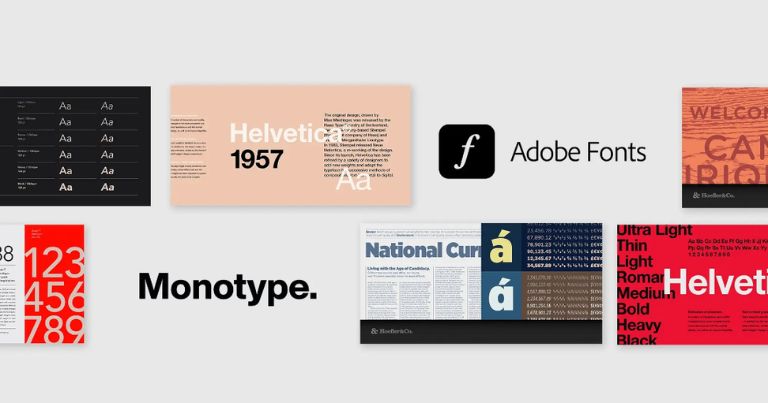
აბა, როგორ ფიქრობთ, რომელია თქვენი შრიფტი? ამ კითხვაზე პასუხის პოვნაში Adobe Acrobat შეიძლება დაგეხმაროთ, რომელმაც ახლახან 13 ყველაზე ცნობილი შრიფტის პიროვნული თვისებები გაგვაცნო. ამ საქმეში კი ხელოვნური ინტელექტი დაიხმარა — 13 განსხვავებული პერსონაჟი შეაქმნევინა, რომლებიც ისეთი შრიფტებითაა შთაგონებული, როგორებიცაა Helvetica, Times New Roman და Comic Sans მანამ, სანამ 1000 ამერიკელს გამოიკვლევდა და ნახავდა, რამდენად შესაფერისი იყო თითოეული მათთვის. როგორც აღმოჩნდა, რესპონდენტთა მეოთხედთან Courier New ყველაზე ახლოსაა.
„ზუსტად ისე, როგორც ზოდიაქო ავლენს პერსონაჟის ბუნებას, ეს შრიფტების პერსონალური ბარათები გვეხმარება, აღმოვაჩინოთ ჩვენი ტიპოგრაფიული სული, დაწყებული Lobster-ის შემოქმედებითი სულისკვეთებით და დამთავრებული Arial-ის პრაქტიკული შარმით. ნება მიეცით შრიფტების ჰოროსკოპს გაპოვნინოთ პერსონაჟი, რომელიც თქვენს ციფრულ იდენტობას წარმოადგენს“, — აცხადებენ Adobe Acrobat-ში.
ახლა კი დროა, თქვენი შრიფტი იპოვოთ: